개발자로 살다 보면, 프로그램 TEXT 글자들과의 싸움이 있답니다.
한 글자만 다르게 봐서, 몇 시간 동안 버그와 씨름했던 시절이 여러 번 있었습니다.
과거 font가 굴림 돋움 정도밖에 없던, "라떼 개발" 시절에는 오타와 씨름이 일상 다반사였죠.
[ 헷갈리는 문자들 ]
- 숫자(0)와 영문 오(O)의 차이
- 소문자 엘 영문(l)과 숫자(1)의 차이
- 콤마(,)와 도트(.)가 차이
- 작은 따옴표=Single Quotation mark(')과 큰 따옴표=Quotation mark(")의 차이
- 콜론(:)과 세미콜론(;)의 차이
개발자로 프로그램을 보다 보면, 글씨의 가독률과 정확률이 얼마나 중요한지를 느낄 수 있습니다.
예전에 제가 자주 사용했던 폰트는 네이버에서 만든 "나눔 고딕 코딩"폰트였습니다.
이 폰트는 14pt이상을 줘야지 가독률이 좋다는 아쉬운 점이 있지만, 가장 많이 애용하는 폰트입니다.
이번에 새롭게 발견된 폰트는 "D2 Coding"폰트인데,
이 폰트 또한 네이버에서 개발자들을 위해 만든 폰트입니다.
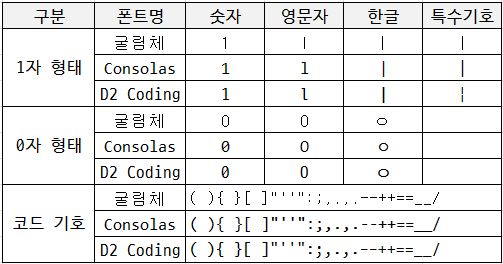
코딩 시 영문자와 숫자뿐만 아니라 한글 유사 기호 간 변별력을 향상되도록 디자인하였습니다. 또한 8~18pt 사이의 크기에서 명확하게 보일 수 있도록 힌팅 처리를 하였습니다.
개인적으로 느끼기에 전반적으로 D2 Coding폰트가 글자의 width가 얇아진 느낌이 많이 듭니다.
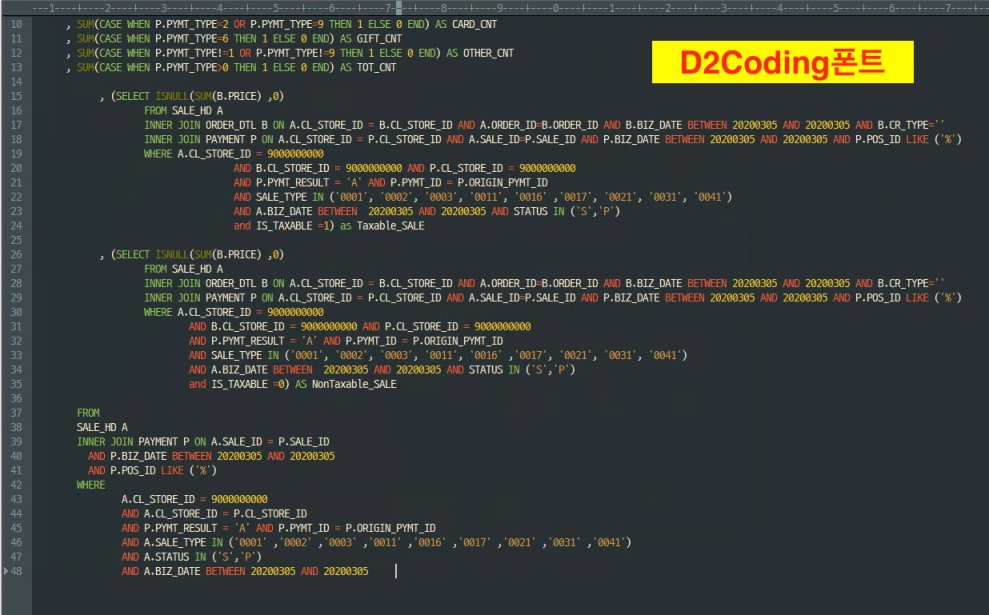
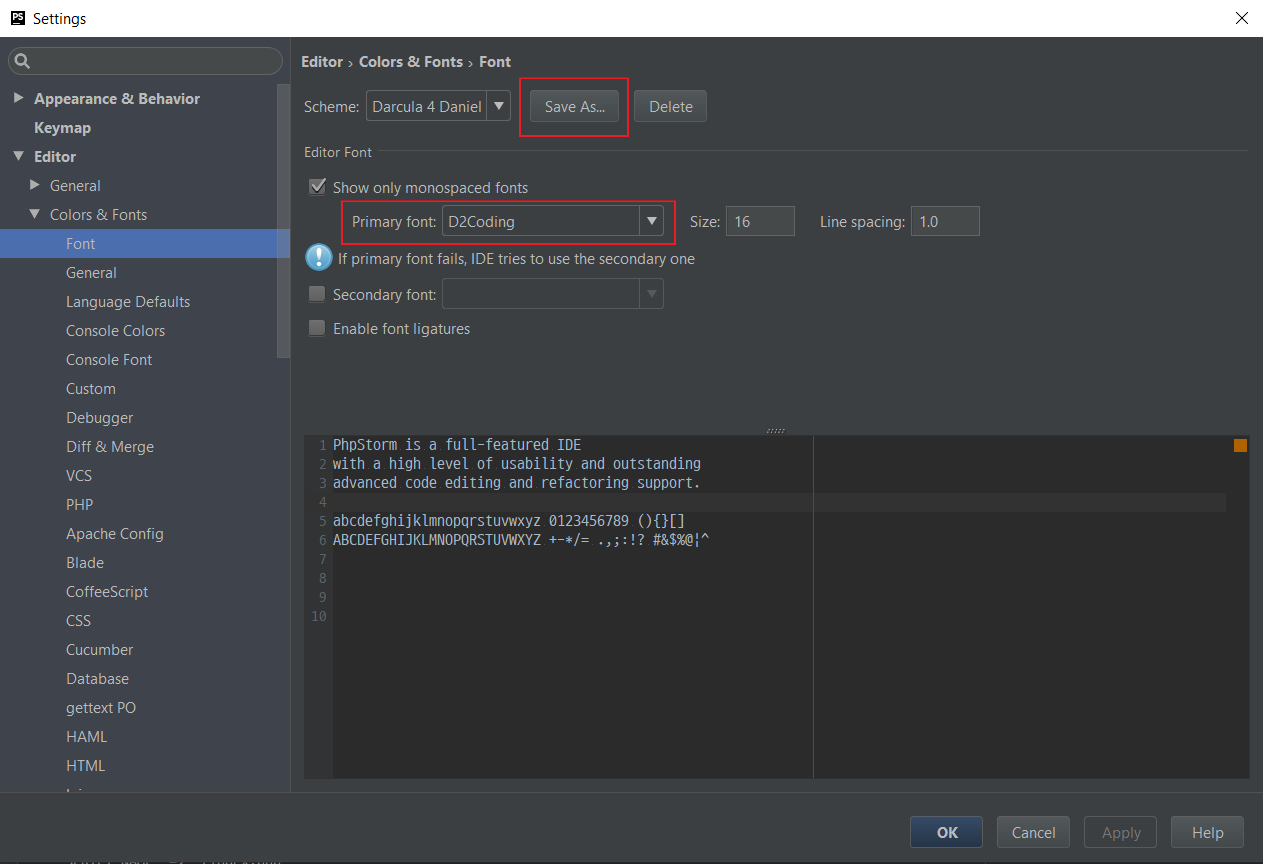
개인적으로 가장 많이 사용하는 OS와 프로그램이
Mac의 PS 많이 사용하다 보니, PS의 기본 폰트인 "Menlo폰트"를 가장 아끼는 편입니다.
윈도우에서 사용하는 Menlo와 비슷한 폰트 => Meslo-font